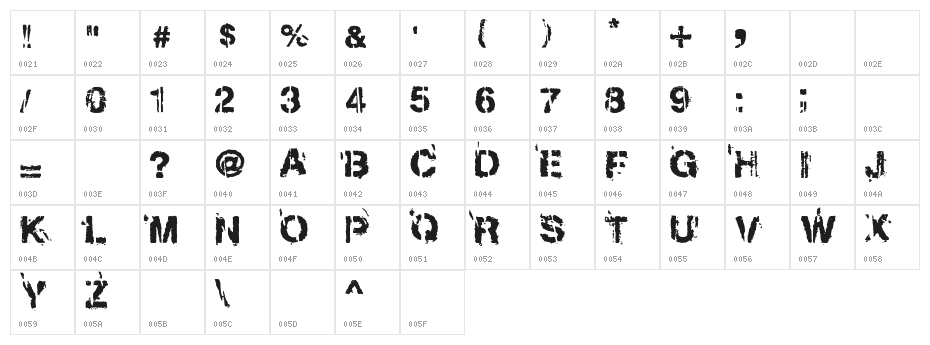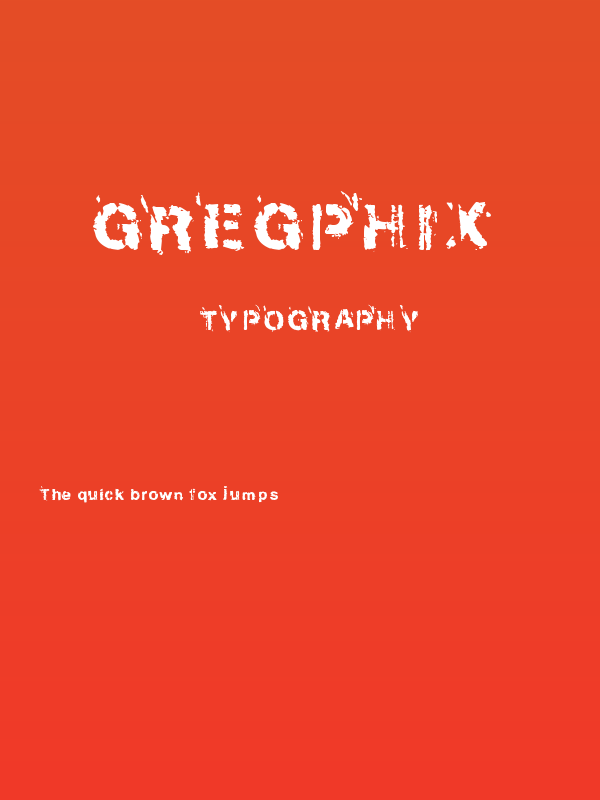
Gregphix Font
✎ Distorted Eroded
| Gesamtstil | Grunge, Vintage |
| Vorgeschlagene Projekte | Ideal for album covers, posters, branding for edgy or vintage-themed products, and any design requiring a rugged, impactful look. |